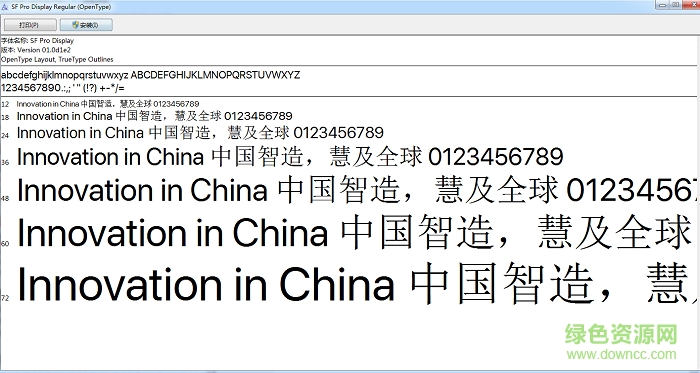
sf pro sc 是什么字体?sf pro sc是一款易读性很强的无衬线字体,干净大气、字距设计恰到好处,用在电子产品的界面非常容易辨识和阅读,欢迎有需要者在绿色资源网免费下载!
无衬线体与汉字字体中的黑体相对应,给人一种休闲轻松的感觉,随着现代生活和流行趋势的变化,如今的人们越来越喜欢用无衬线体,因为他们看上去“更干净”。